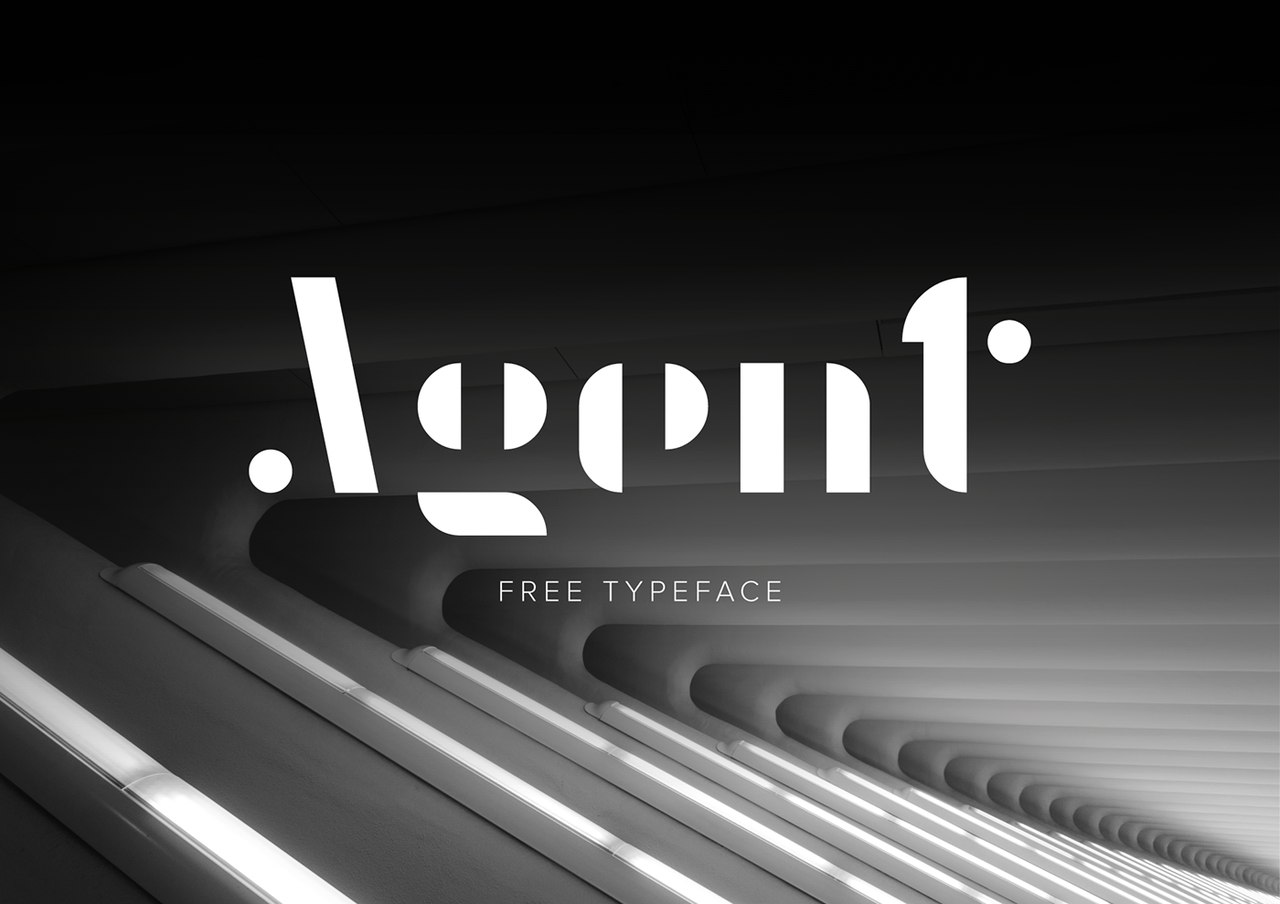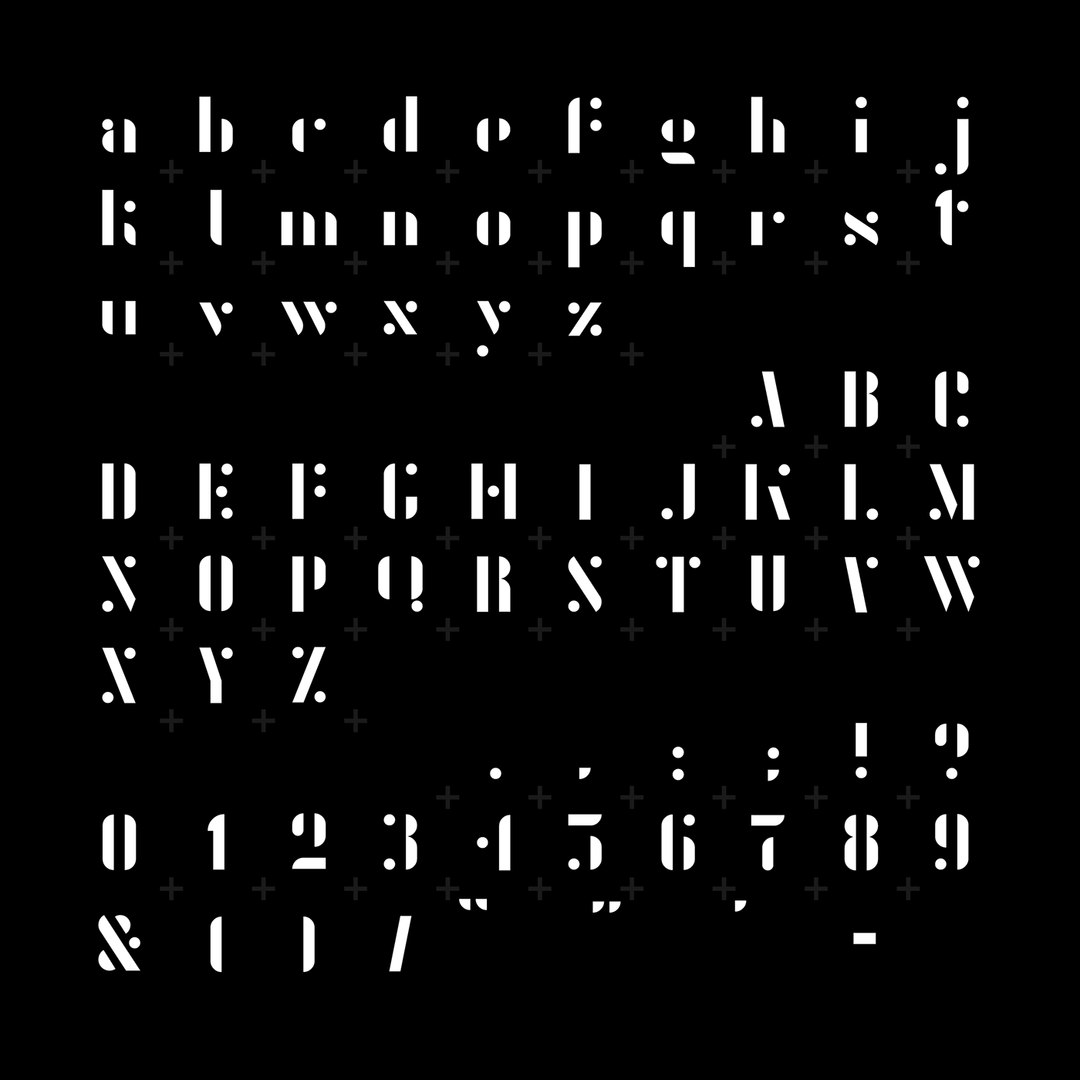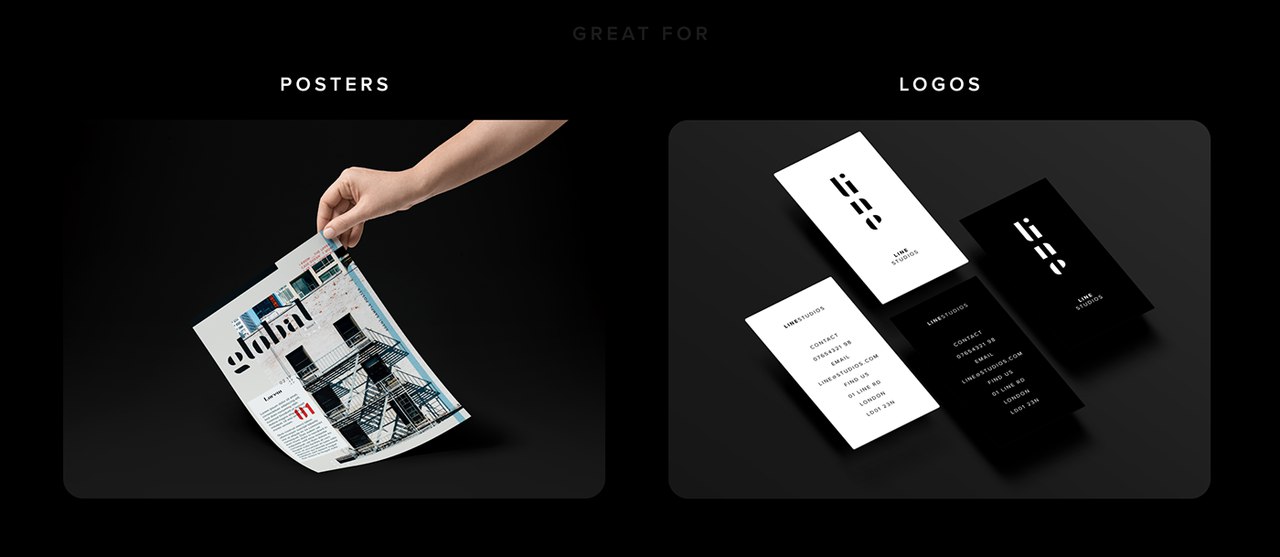
Шрифт: Agent (Латиница)
Автор: Mark O’Neill (behance.net/markoneill) из Великобритании.
Интересный акцидентный шрифт. Отлично пойдет для лого, плакатов, листовок, фирменного стиля и т д.